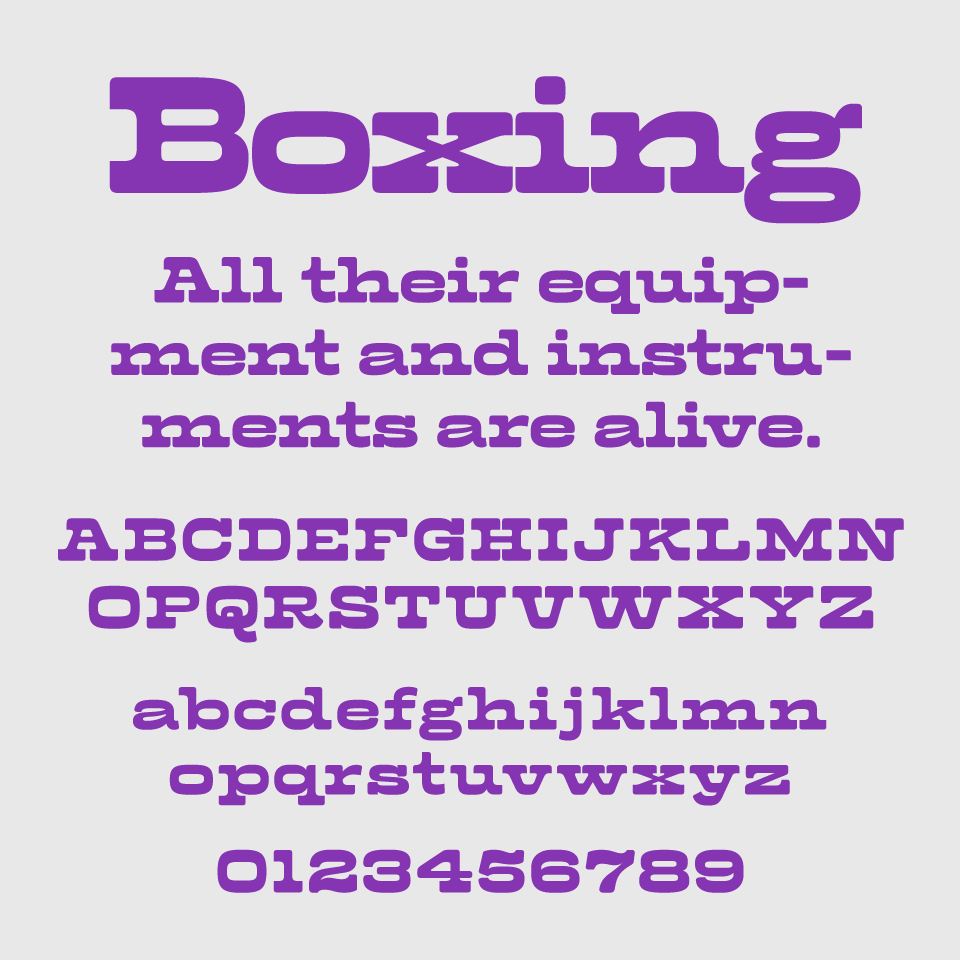
Boxingフォントは、ヴィンテージ感と重厚感を併せ持つスラブセリフ体で、どっしりとした構造と丸みのある角が特徴なフォントです。
ちょっとレトロなタイプライター風の印象を残しつつも、丸めた端や装飾的なクロスバーが可愛らしさも感じられるデザインです。
文字の線が太く、コントラストが控えめなため、力強さとフレンドリーさの両立が感じられフォントの名前から、スポーツ感も感じられるフォントとなっています。